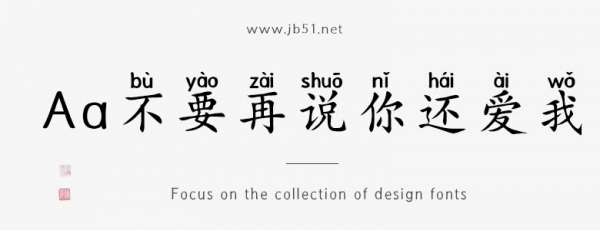
Aa不要再說(shuō)你還愛(ài)我由Aa字庫(kù)出品的藝術(shù)字體,字體筆觸粗實(shí),字形端正,適合應(yīng)用于藝術(shù)設(shè)計(jì)、平面宣傳設(shè)計(jì)、網(wǎng)頁(yè)設(shè)計(jì),書(shū)法字帖等領(lǐng)域。有需要的朋友快來(lái)本站下載使用吧。